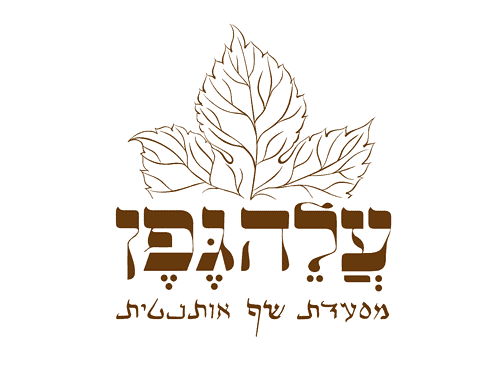
Mugrabi is divided into two complementary versions: Mugrabi Display for headlines and Mugrabi Text for running text.
הוא מאופיין בקונטרסט רב בין הקווים האופקיים לאנכיים, ובמבנה מרובע ומעוטר.
Mugrabi originated from a classic Hebrew typeface found in the Bezalel catalog under the name “Sefardi.” Its revival was inspired by vintage posters for films shown at Tel Aviv’s iconic Mugrabi Cinema.
• על אודות פונט מוגרבי דיספליי
הרחבה דו־לשונית לאחד הפונטים האהובים בספריית אאא. המשפחה נחלקת לשתי גרסאות משלימות: Mugrabi Display לכותרות, ו־Mugrabi Text לטקסט־רץ.
מקורה של מוגרבי באות עברית קלאסית מתוך קטלוג בצלאל, שם הופיעה בשם ״ספרדי״. חידוש האות נשען על כרזות ישנות של סרטים שהוקרנו בקולנוע מוגרבי בתל־אביב. אף שמעט ידוע על זהות מעצבה, ניכר בה קשר לאות היוגנדסטיל שרווחה בדפוס היהודי באירופה.
הגרסה החדשה כוללת גם מערכת לטינית מקורית, ושומרת על המתח הייחודי בין הקווים האנכיים והאופקיים, תוך התאמה לצרכים הטיפוגרפיים של ימינו.